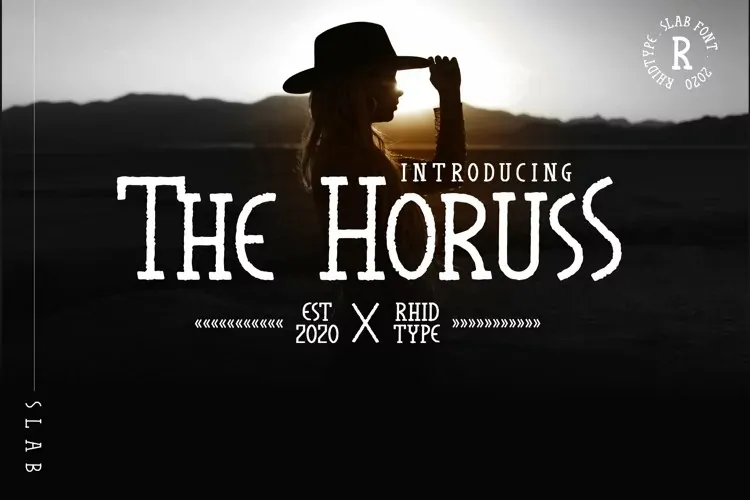
A fonte The Horuss Font é uma seleção única entre as Slab Serifs. Ela se destaca com sua textura stamp vintage, criada por RHID TYPE e compartilhada no site 99designs. Esta font é caracterizada pela sua aparência robusta e impulsionadora, garantindo que seus projetos possam destacar-se no espaço de design digital e impressão. Perfeita para adicionar um toque moderno a mensagens publicitárias ou logos, também se encaixa perfeitamente em trabalhos digitais e arte criativa. O seu aspecto robusto faz dele uma escolha sólida e convincente para qualquer aplicação visual onde seja necessário transmitir confiança e força.